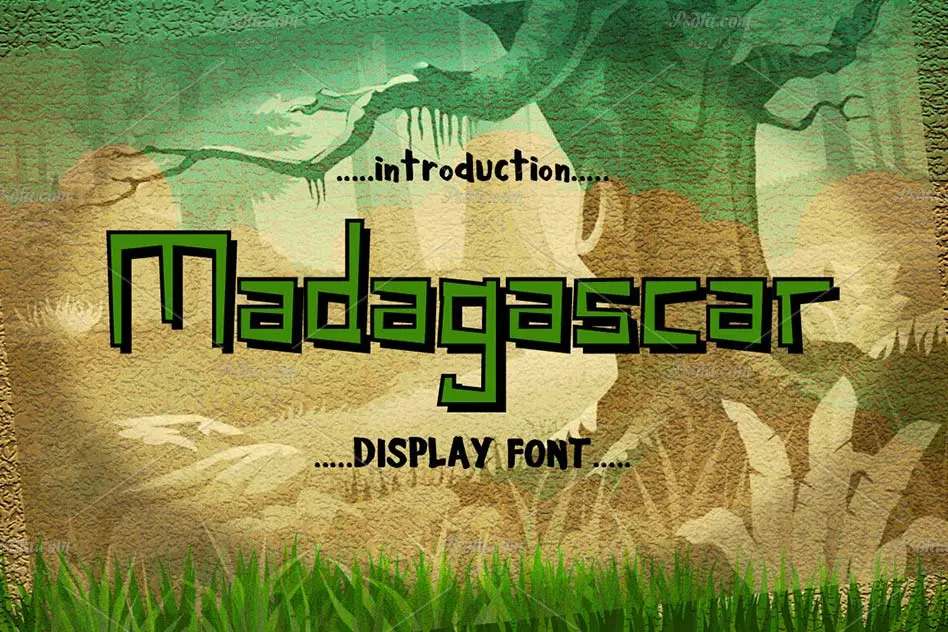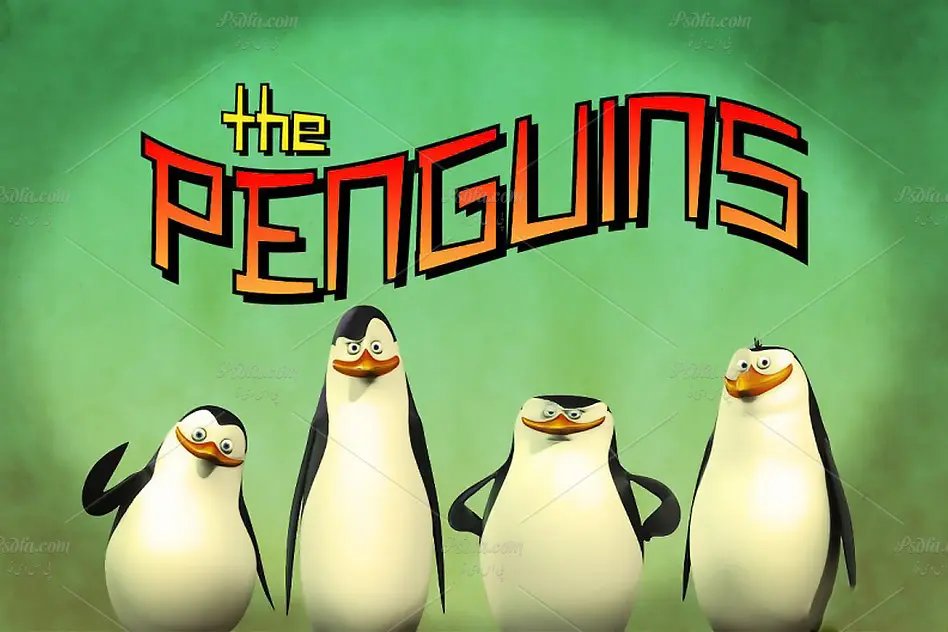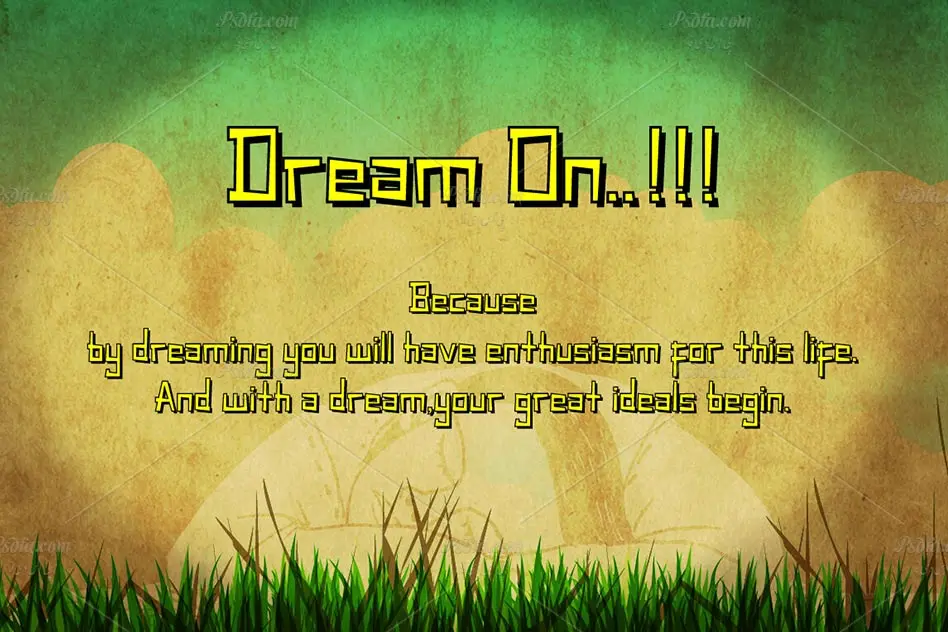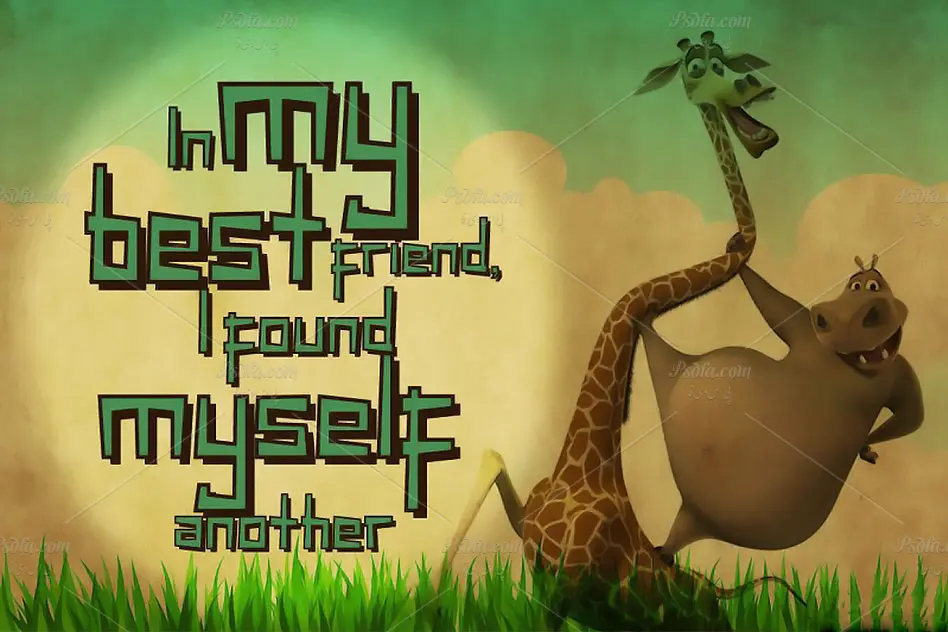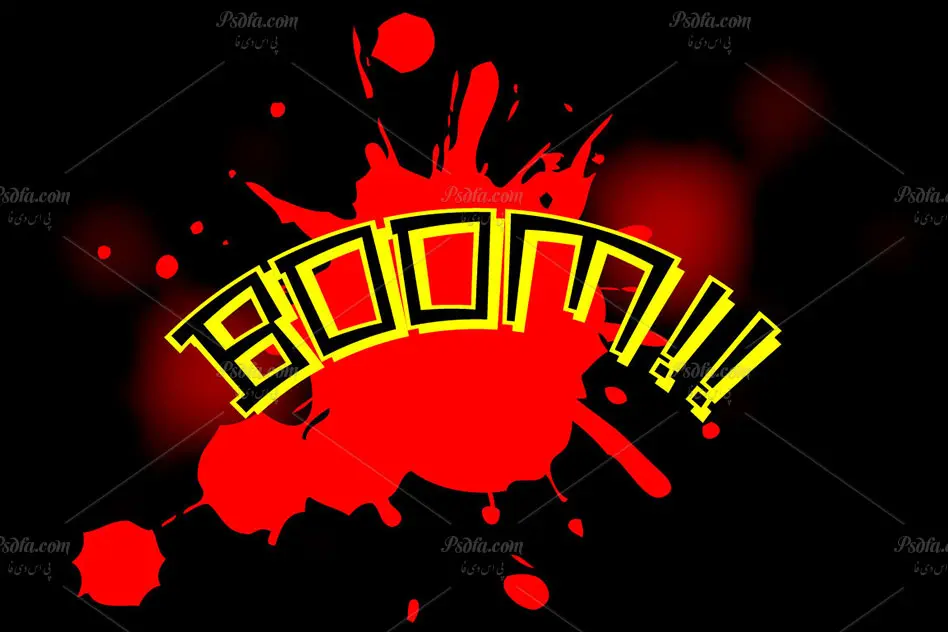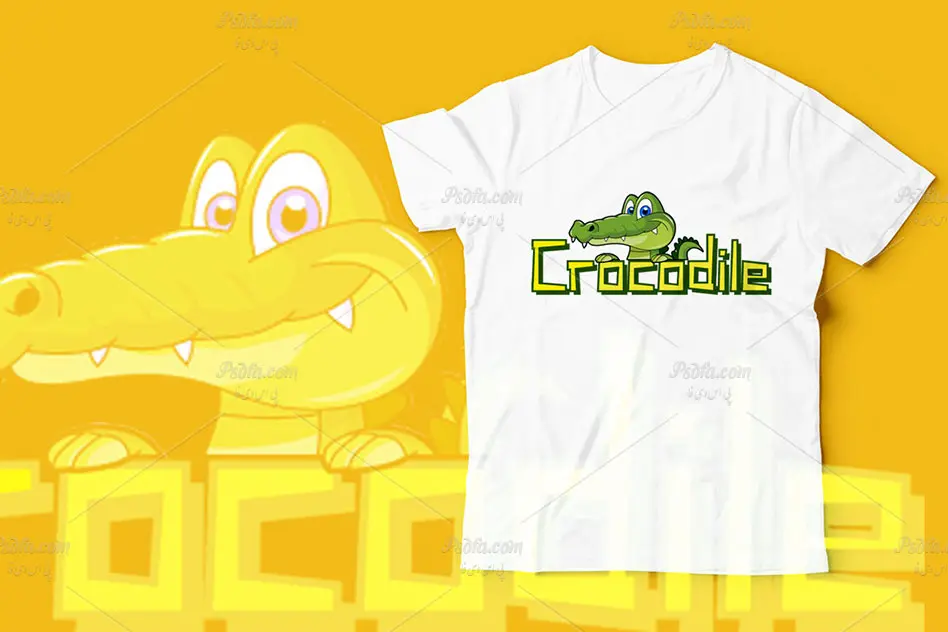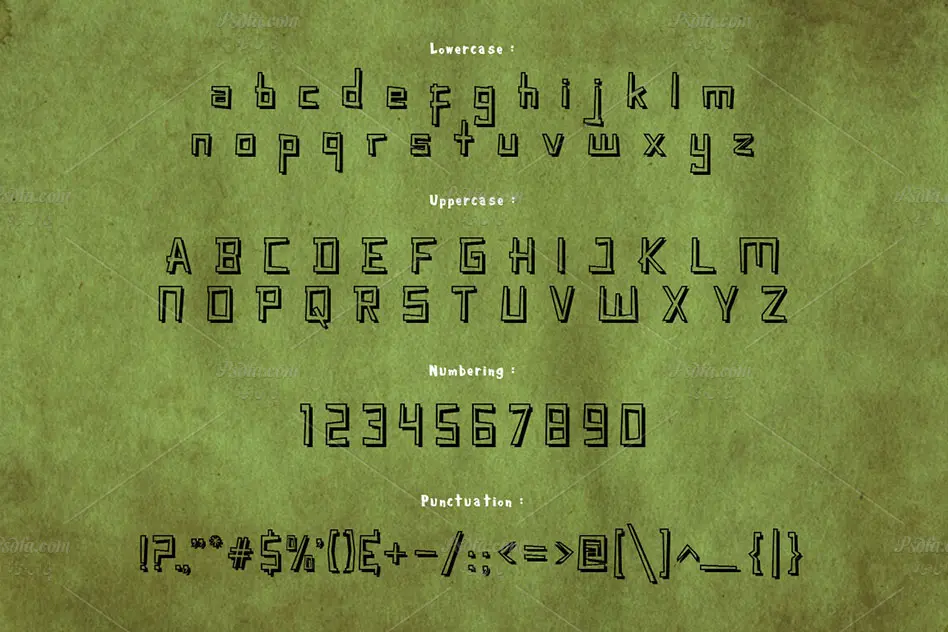
در این مطلب شاهد فونت نمایشی و کودکانه ماداگاسکار (Madagascar Display Font) مناسب جهت استفاده در طرح های گرافیکی به خصوص طرح های فانتزی و کودکانه می باشید. این فونت در قالب 2 فایل otf و ttf بر روی سایت بارگذاری شده است که با نصب یکی از این دو فرمت در پوشه فونت های سیستم قادر به استفاده از آن در تمام نرم افزارهای گرافیکی و ویرایشگر متن خواهید بود. فونت Madagascar در وزن معمولی (Regular) طراحی و ایجاد شده است که از آن می توان در طراحی انواع پوستر ، تراکت ، بروشور ، طرح های کودکانه و دیگر طرح های گرافیکی استفاده نمود.
- نام فونت : Madagaskar
- وزن : معمولی (Regular)